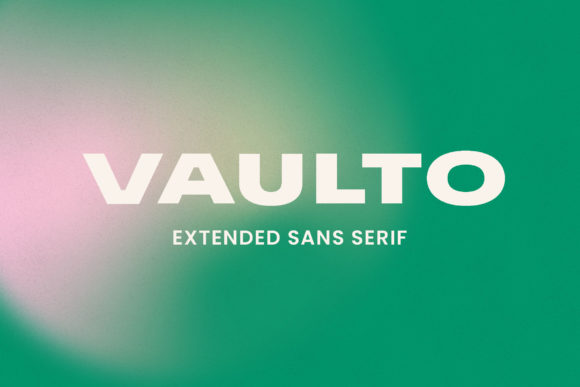
Creativefabrica Vaulto Black Font
[Creativefabrica] Vaulto Black Font
Vaulto Black - это простой, толстый и жирный шрифт без засечек.
Его легко подогнать под невероятно большой набор проектов, поэтому добавьте его в свои творческие идеи и обратите внимание на то, как он выделяет их на фоне других!